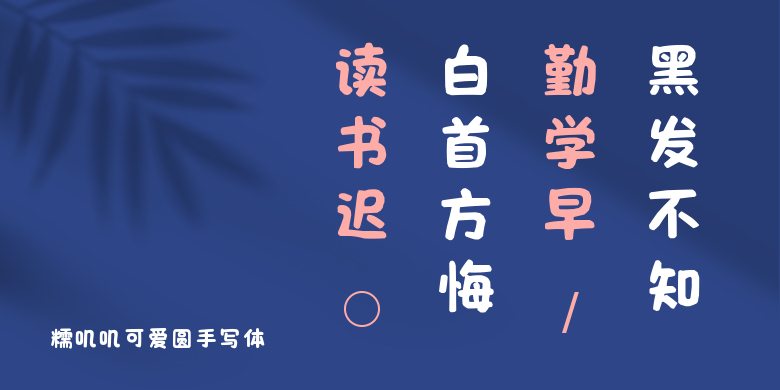
糯叽叽可爱圆手写体
糯叽叽可爱圆手写体,这款字体结构工整、笔画清晰,兼顾美观与易读性,适用于标题、正文、海报、包装、LOGO 等多种场景。字形优雅稳定,风格百搭耐看,适配日常排版与创意设计,让文字呈现更舒适、更具质感。糯叽叽可爱圆手写体一笔一画,皆是细节,以均衡的比例、流畅的线条打造舒适视觉体验,字形端正大气,风格简约现代。无论是商业设计、品牌宣传还是日常排版,都能轻松驾驭,让文字更有格调与力量。糯叽叽可爱圆手写体字体下载。